楷体又被称做是活体,是一种模仿手写习惯的一种字体,笔画挺秀均匀,字形端正,广泛地用于学生课本、通俗读物、批注等。楷体比起屏幕显示领域更多的是出现在创作设计上。小编今天要给大家推荐的是经过改善后可以广泛应用的的三款楷体,一起看看下面这些图片字体吧。
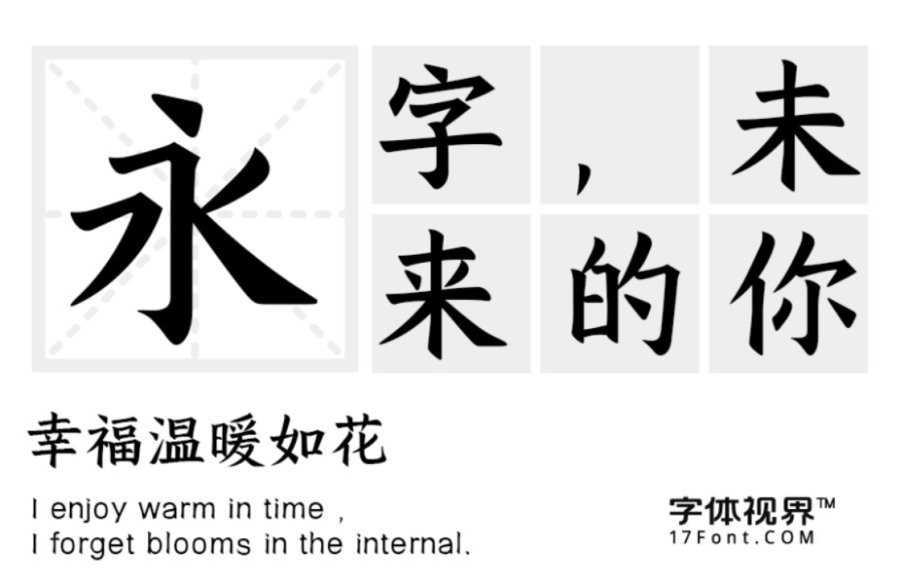
三极拙楷简体:这款字体以现行楷书为基础,笔画利落分明,字形端正,结构严谨。起笔收笔朴拙有力,大巧若拙,寓巧于拙,尽显朴拙之美。适用于logo、印刷、正文、屏显等多种设计领域。
汉标智造国楷:这款字体书法气息浓厚,结字潇洒俊逸,运笔行云流水,气韵生动。适用于文艺类的书刊、品牌广告和产品包装设计,以及社交网络的个性化用字。
汉标榜样毛笔楷体:这款字体遵循着书法的书写规范风格气质端庄温润,又富有现代感十足的艺术气息。起笔收笔干净利落、字形清晰、易于字体识别,清新自然却不失力量感。适用于中国风设计、海报设计、标题、广告、印刷等广泛设计领域。